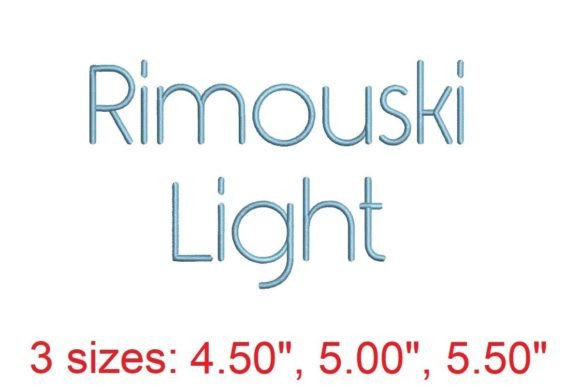
Rimouski Light Embroidery Font
Mencari elemen reka bentuk yang sesuai boleh menjadi mencabar, tetapi Rimouski Light Embroidery Font menawarkan koleksi luar biasa yang menaik taraf karya anda serta-merta.
Dicipta dengan ketepatan, Rimouski Light Embroidery Font menyediakan vektor yang bersih, tipografi yang licin dan lesen komersial untuk ketenangan fikiran.
Sama ada anda mencipta produk POD (Print on Demand), jemputan perkahwinan atau grafik media sosial, Rimouski Light Embroidery Font amat bersesuaian.